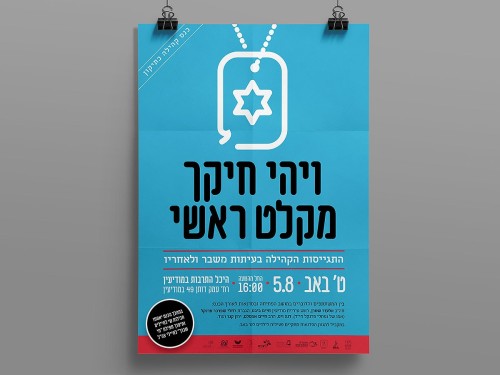
על אודות פונט סטנגה
סטנגה הוא פונט דו־לשוני צעיר ואנרגטי בעל מבנה אותיות צר ויציב. הוא מאופיין בקצוות מעוגלים וקימורים רכים השוברים את הנוקשות ומאזנים אותו. זהו פונט אוורירי ונעים לקריאה העובד נהדר בכותרות, לוגואים, שילוט וקטעי טקסט קצרים.
פונט סטנגה עוצב על־ידי ערן בכרך בשנת 2012. מאז ועד היום הפונט זכה לפופולאריות רבה וכיום ניתן לראות אותו מופיע על אריזות מזון, תדמיות, תכניות טלויזיה, שילוט ועוד. בשנת 2021 עיצבה אנה חורש תוספת של אנגלית ותמיכה ב־219 שפות לטיניות – באותיות Uppercase, וכן נוספו לו שני משקלים חדשים: אולטרה־לייט ודמי־בולד.
OpenType Features
- חלופות סגנוניות ₪ ← ₪
- 0 ← 0
- ← ← ←
- ליגטורות סודיות אשכרה ← אשכרה
- חלופות הקשריות מותג ← מותג
- ניקוד מדוקדק קֳ ← קֳ